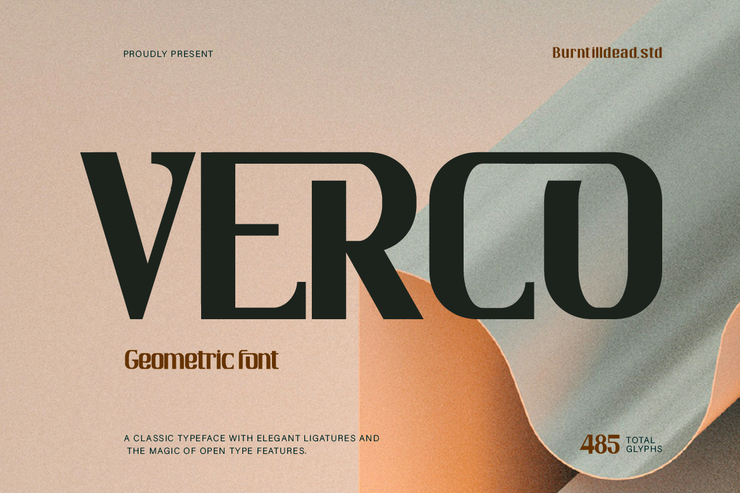
Verco Elegant Modern Stilvoll Dekorativ Englische Schrift
Verco ist eine raffinierte, moderne, dekorative englische Schrift mit glatten, klaren Strichen und ausgewogenen geometrischen Buchstabenstrukturen. Ihr minimalistischer und raffinierter Stil bietet ein hochwertiges visuelles Temperament, das sich für zeitgenössisches Branding und kommerzielles Design eignet. Die Schrift zeichnet sich durch saubere Kurven und scharfe Konturen aus und verbindet Einfachheit mit eleganter Textur, um sich in verschiedenen visuellen Kreationen abzuheben. Sie eignet sich hervorragend für Markenlogos, Modeposter, Web-Schlagzeilen, E-Commerce-Banner, Produktverpackungen und Social-Media-Grafikdesign. Komplett mit Groß- und Kleinbuchstaben ist sie hochgradig skalierbar und lässt sich leicht an Farben, Größen und Layouts anpassen, ohne empfindliche Details zu verlieren. Ideal für Grafikdesigner, Kreativstudios und kommerzielle Markenprojekte, um erstklassige visuelle works.Free für den gewerblichen Gebrauch zu schaffen / Kein Copyright 1